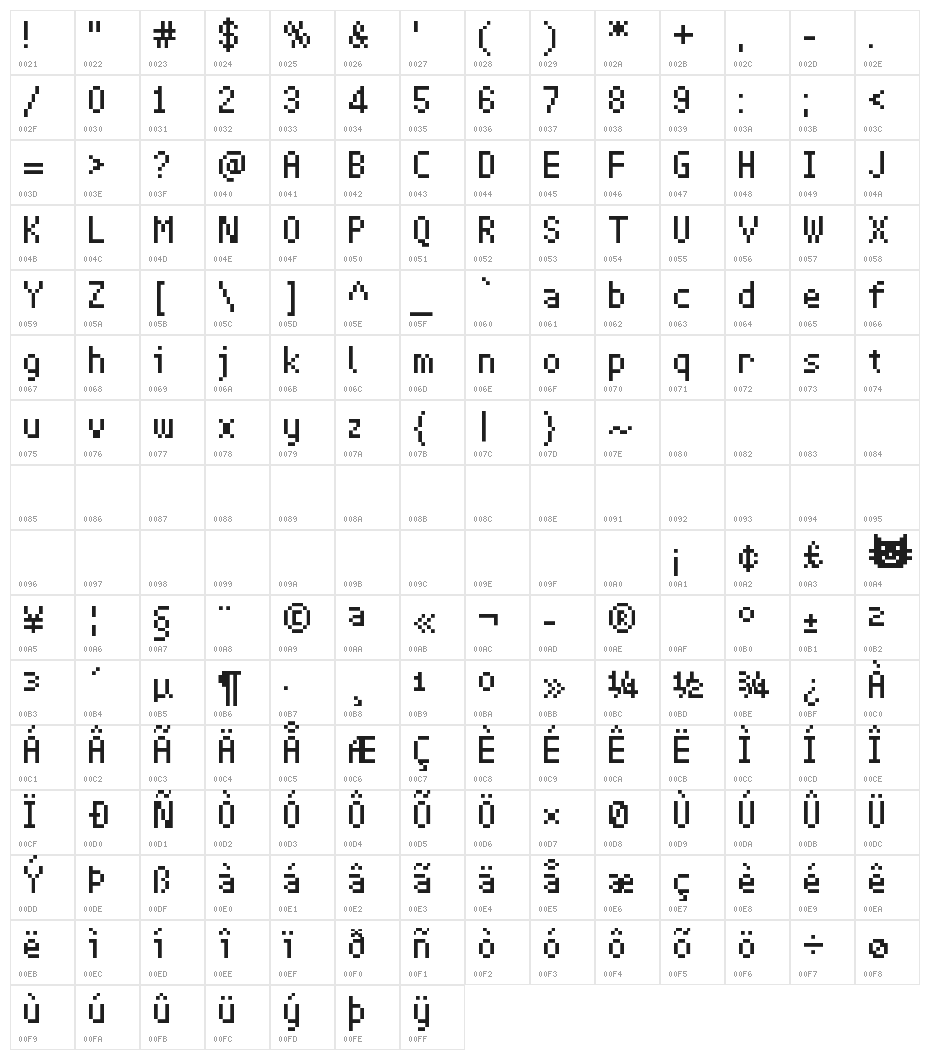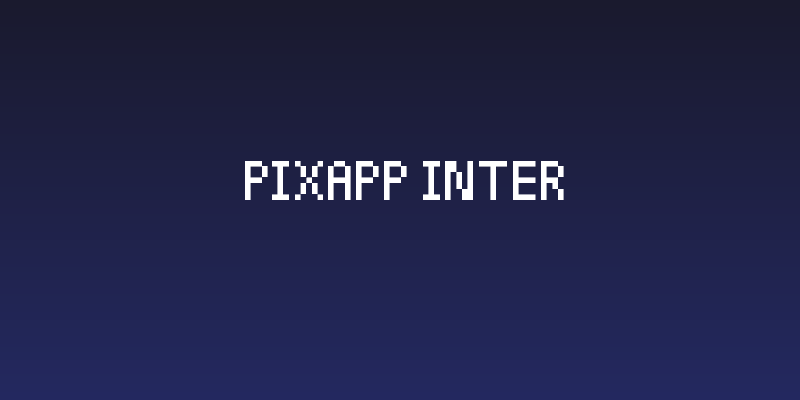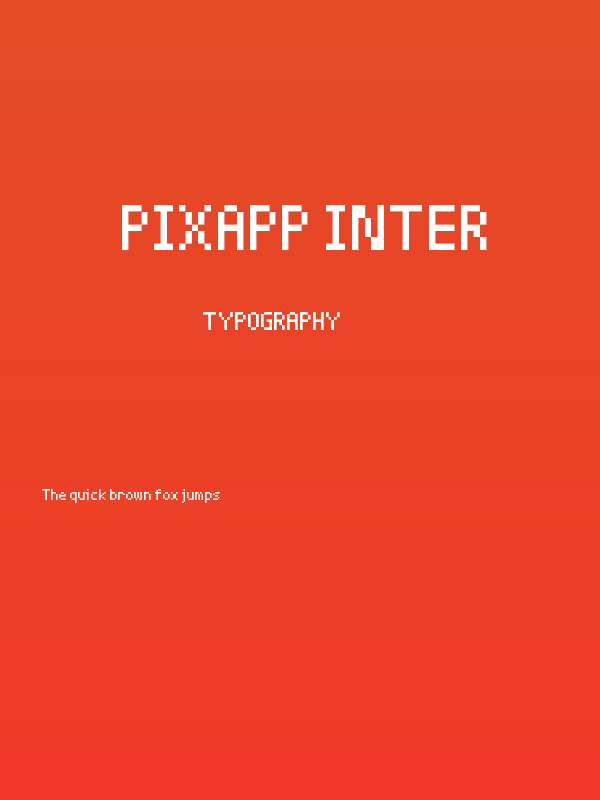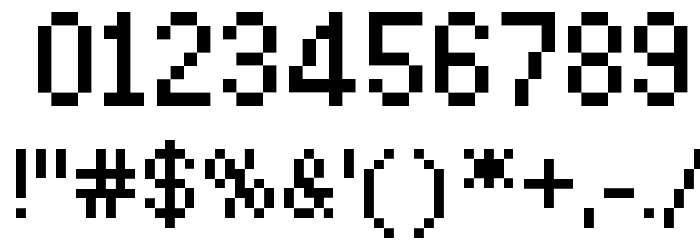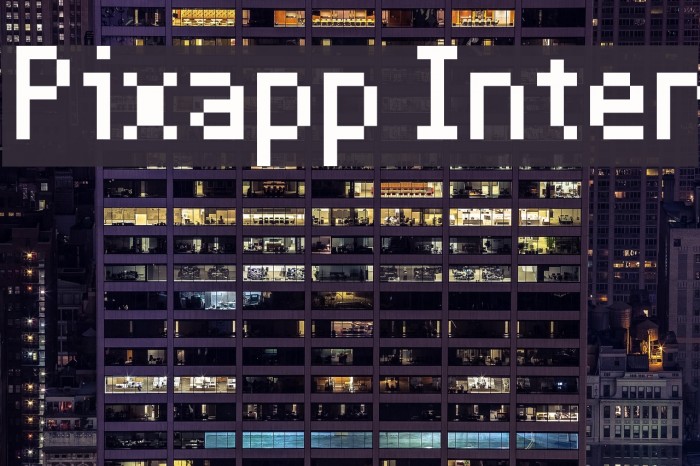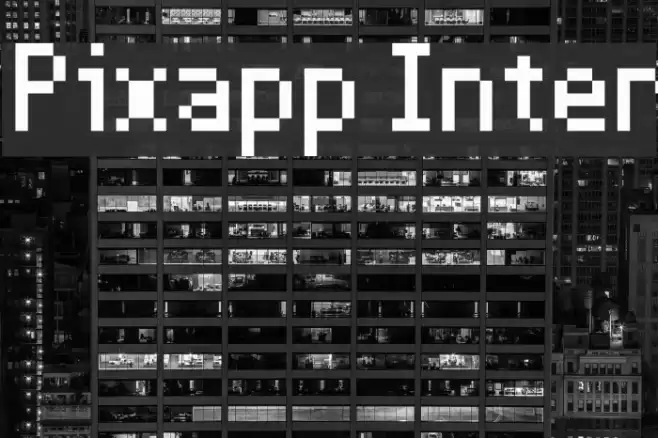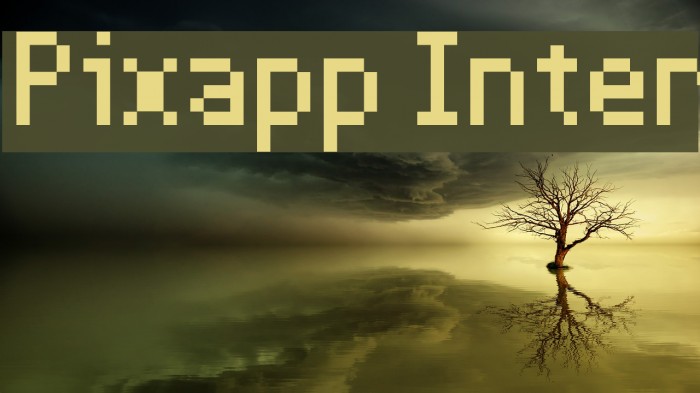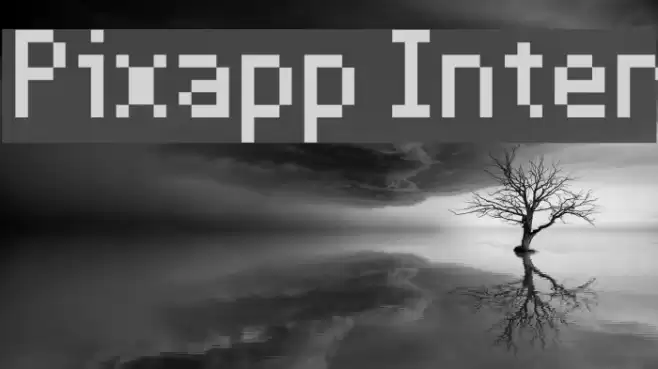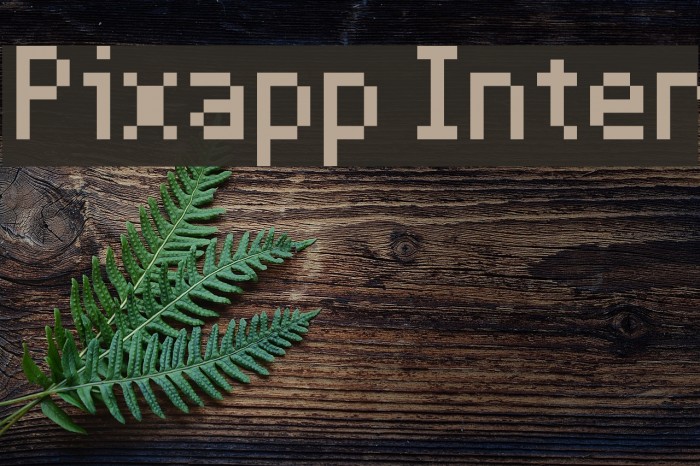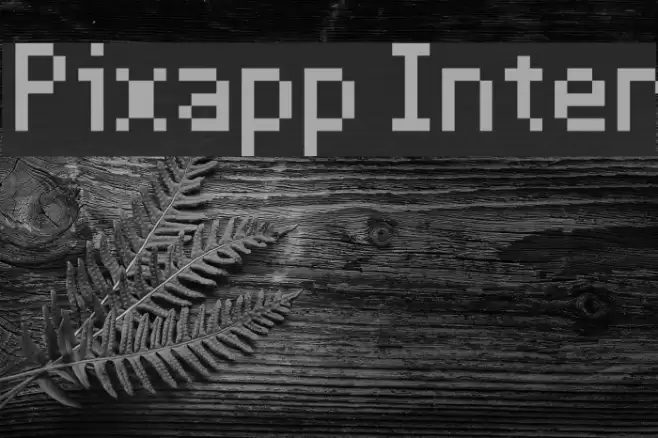
Pixapp Inter Font
| Nume | Pixapp Inter |
| Categorii | Pixel |
| Stil general | Retro, Digital |
| Caz de utilizare | Logos, Headlines, Digital Art |
| Proiecte propuse | Ideal for video game design, digital art projects, retro-themed websites, and tech-related branding. |
| Autor | Fonts by Matt McInerney |